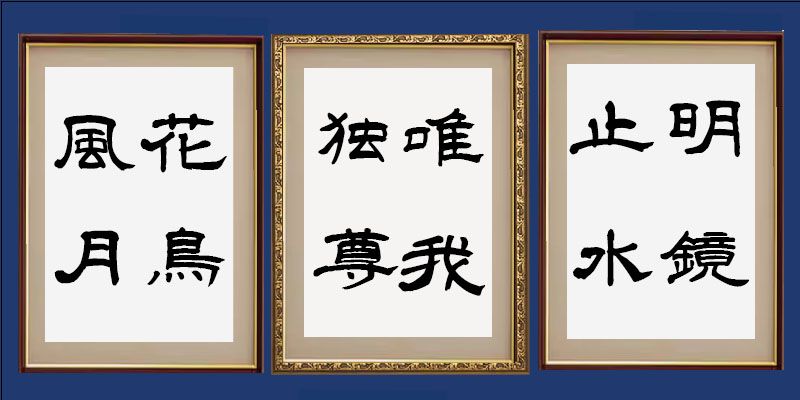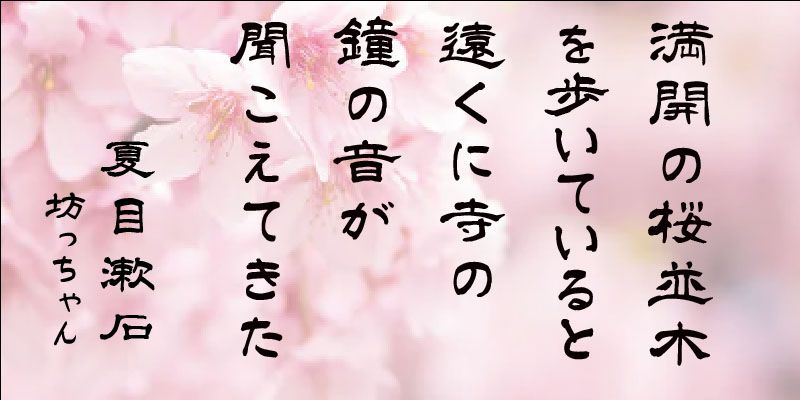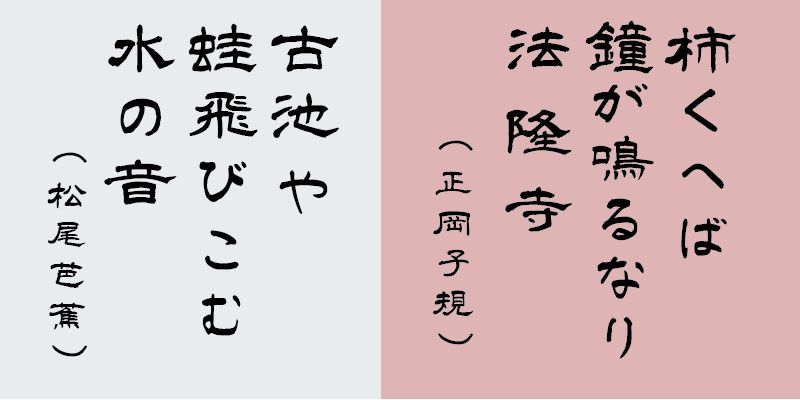
Дизайнер, ориентируясь на стиль надписи Cáo Quán Bēi, расширил и выровнял символы, чтобы передать стабильность и спокойствие оригинального письма. Ему удалось создать семейство шрифтов, сохраняющих аутентичность и высокое качество традиционного канцелярского письма.
Буквенно-цифровые символы, символы хираганы и катаканы, включенные в каждый шрифт семейства, выполнены в виде пропорциональных глифов, каждый из которых имеет собственную ширину символов.
Хакусю Накамото, работая в области каллиграфии больше 60 лет, создал каллиграфические шрифты с красивыми и искусно написанными кистью формами букв. Он работает профессиональным каллиграфом и предлагает индивидуальные услуги для клиентов с различными потребностями. Используя дизайны Накамото, вы сможете лучше познакомиться с искусством традиционной каллиграфии.